2023 年 27 种最佳 Procreate 字体(免费和付费)
已发表: 2023-08-23您是一名平面设计师,希望用完美的字体来提升您的项目吗? 好吧,不用再犹豫了,因为我们专门为您整理了 27 种最佳 Procreate 字体列表。 但您可能想知道,我怎么知道这些字体确实是最好的?
在本文中,我们不仅会向您提供可用的顶级 Procreate 字体的概述,还会为您提供有关每种字体的一些有趣的统计数据和事实,以帮助您做出明智的决定。
我们知道选择正确的字体可能是一项具有挑战性的任务,因此我们为您进行了研究,并精心挑选了其中的精华。
无论您是在进行徽标设计、社交媒体图形还是网站布局,我们都能满足您的需求。 我们列表中的每种字体都因其独特的风格、多功能性和整体影响力而经过精心挑选。
另外,我们甚至会为您提供一些有关如何在设计项目中充分利用这些字体的提示。 那么,让我们深入探索 Procreate 字体的不可思议的世界!
最佳高级 Procreate 字体
希望将您的 Procreate 项目提升到新的水平? 我们精选的最佳优质 Procreate 字体就是您的最佳选择。 这些令人惊叹的字体一定会提升您的设计并使其在人群中脱颖而出。
不要错过在我们的文章中查看和发现这些奇妙字体的机会。
加尔盖
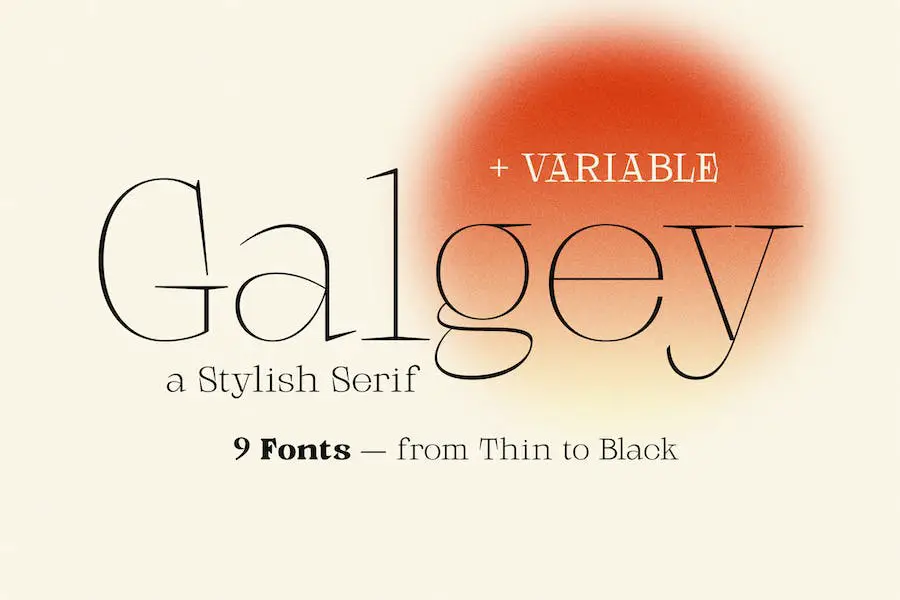
Galgey 是一种时尚的衬线字体,提供 9 种不同的粗细,从细到黑色。 凭借其简洁和现代的设计,无论您是在处理印刷材料还是数字创作,它都是各种设计项目的完美选择。
Galgey 集中的字体经过仔细调整,确保字母之间的最佳间距,并且它们可以在任何程序中使用,无需额外的插件或软件。
该字体集提供了多种选项,允许您尝试不同的粗细和样式,以获得适合您的项目的外观。 无论您想要精致优雅的美感,还是大胆而有影响力的设计,Galgey 都能满足您的需求。
Galgey 的主要优势之一是它的简单性。 简洁的线条和简约的字体使其即使在较小的尺寸下也非常清晰易读。
这使得 Galgey 成为编辑布局中正文以及需要产生强烈影响的标题和标题的绝佳选择。 该字体的现代和永恒的设计确保它永远不会过时。
勇士
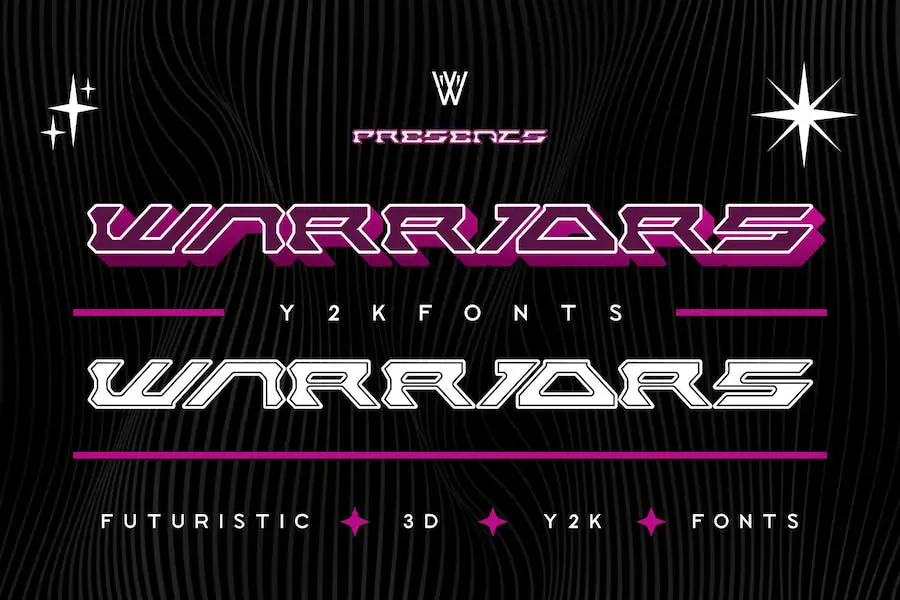
Warriors 是一种散发着未来主义和赛博朋克风格印象的字体,使其成为创建引人注目的海报设计的完美选择。 其独特的功能和美观使其有别于市场上的其他字体。
Warriors 字体拥有现代而前卫的外观,具有锐利的角度和流畅的线条。 这种字体旨在吸引注意力并在任何项目中发表声明。
无论您是在制作活动、促销海报还是平面设计作品,《Warriors》都能增添一丝前卫的魅力。
勇士队的突出特点之一是它的多功能性。 这种字体可用于多种设计,从粗体标题到时尚的正文。 其时尚且充满未来感的外观使其成为科幻或科技主题项目的绝佳选择。
此外,它还可以与各种配色方案完美配合,让您可以尝试并创造出视觉上令人惊叹的作品。
有缺陷的
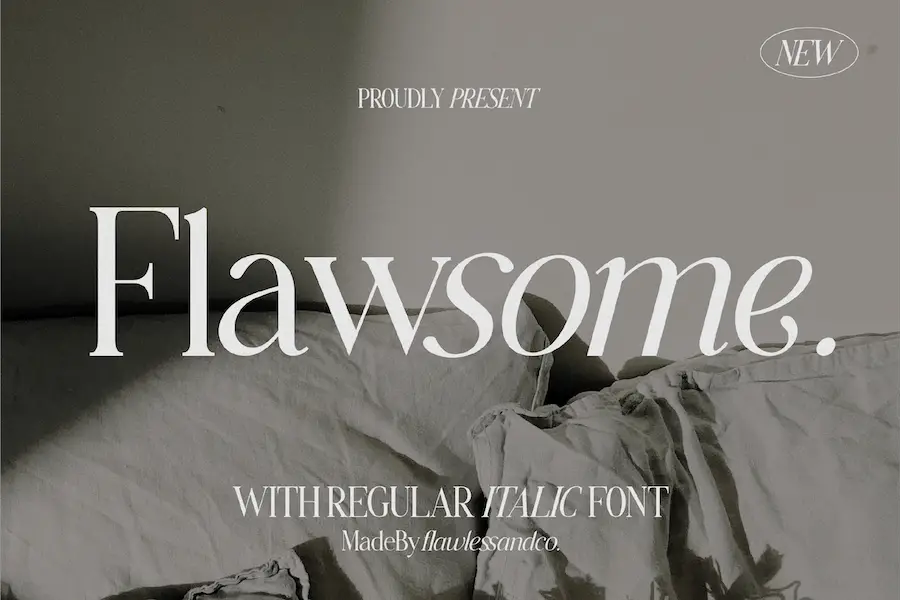
隆重推出 Flawsome,这是一种常规斜体衬线字体,可为您的设计项目带来现代和千禧一代的感觉。 这种字体组合用途广泛,可以在各种平台上使用。
凭借其优雅奢华的外观,它非常适合创建徽标和品牌材料。
Flawsome 字体具有区别于其他字体的独特魅力。 其规则的斜体风格为您的设计增添了一丝精致和创造力。 无论您是从事专业项目还是个人项目,这种字体都会提升整体外观和感觉。
Flawsome 的一大优点是它与 Canva、Procreate 和 Cricut 等流行设计软件的兼容性。 这使得它非常易于使用并融入您的设计工作流程。 您可以使用此字体轻松创建令人惊叹的图形、数字艺术,甚至剪贴画。
爱无所不在
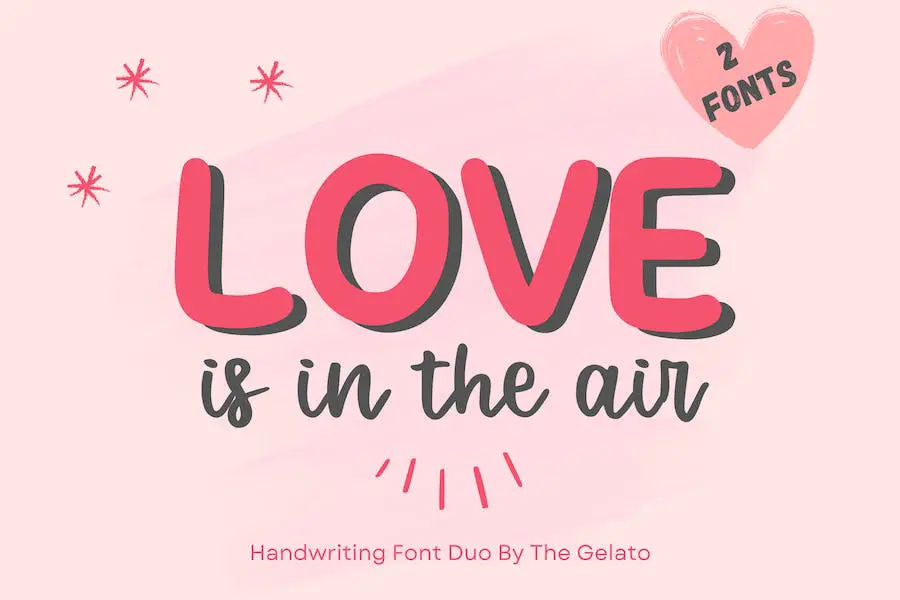
Love Is In The Air 是一套字体配对集,结合了两种令人惊叹的手写书法和单线粗体手写字体。 借助这款字体组合,您可以轻松为您的设计项目增添一丝优雅和浪漫。
该集中的第一个字体是一个漂亮的手写书法字体。 它散发着女性气质和优雅感,非常适合制作婚礼请柬、情书或任何需要浪漫气息的项目。 其流畅的笔触和精致的曲线将立即提升您的设计。
第二种字体是单线粗体手写字体。 它为您的设计增添了现代感和现代感,非常适合增添一些冲击力和风格。
无论您是在制作徽标、品牌还是社交媒体图形,这种字体都将使您的文本以其大胆而自信的外观脱颖而出。
《Love Is In The Air》中的两种字体完美互补,在优雅与大胆之间创造出和谐的平衡。 无论是一起使用还是单独使用,它们都会为您的设计增添独特而引人注目的元素。
韦伯鲁什
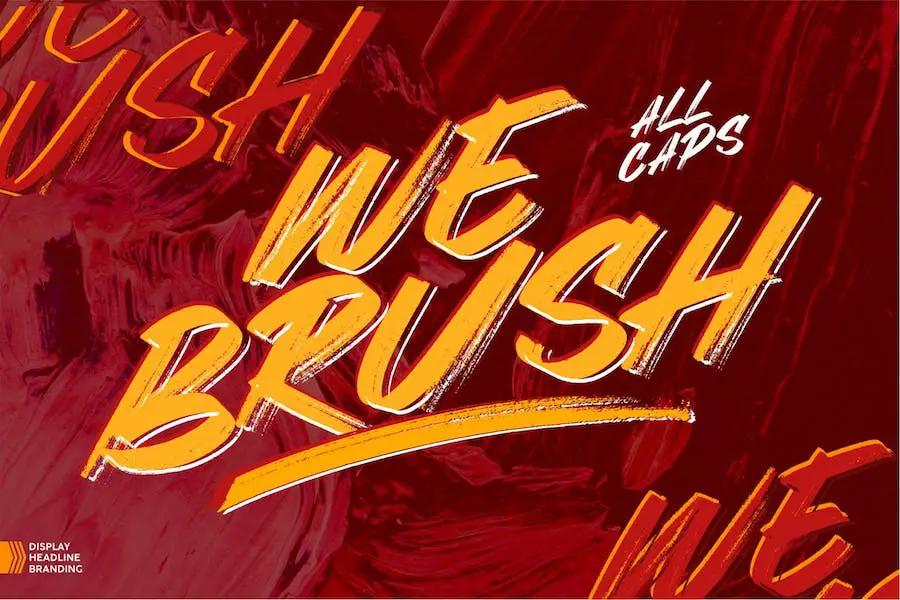
隆重推出 Webrush,这是一款 Procreate 字体,它将迷人的曲线与清新的城市边缘融为一体。 这个时尚的脚本非常适合增强您的徽标设计、商品和社交媒体帖子。 凭借其引人注目的吸引力,Webrush 一定会让您的项目脱颖而出。
Webrush 的优点之一是它的多功能性。 无论您是想创建一个现代徽标还是为您的社交媒体帖子添加一丝优雅,这款字体都能满足您的需求。 其迷人的曲线赋予其独特而时尚的外观,非常适合任何设计项目。
Webrush 的另一个优点是它能够为您的设计添加个人风格。 这种字体的手写感觉为您的作品增添了真实感和温暖感,使其更能引起观众的共鸣和吸引力。
它是在您的设计中添加个人引言或信息的完美选择。
格罗克标记
Grock Marker 是一款时尚的画笔标记字体,非常适合为您的创意项目添加自然的触感。 这种独特的字体将手写字体与戏剧性的动作相结合,为您的设计带来精美的手写外观。
无论您正在制作徽标、海报还是任何其他创意项目,Grock Marker 都会添加您正在寻找的额外风格。 其自然有机的风格非常适合吸引注意力并给人留下持久的印象。
凭借其易于使用的格式,您可以使用 Procreate 将 Grock Marker 无缝融入您的设计中。 告别无聊的通用字体,并利用 Grock Marker 的魅力和个性提升您的项目。
吉布拉内
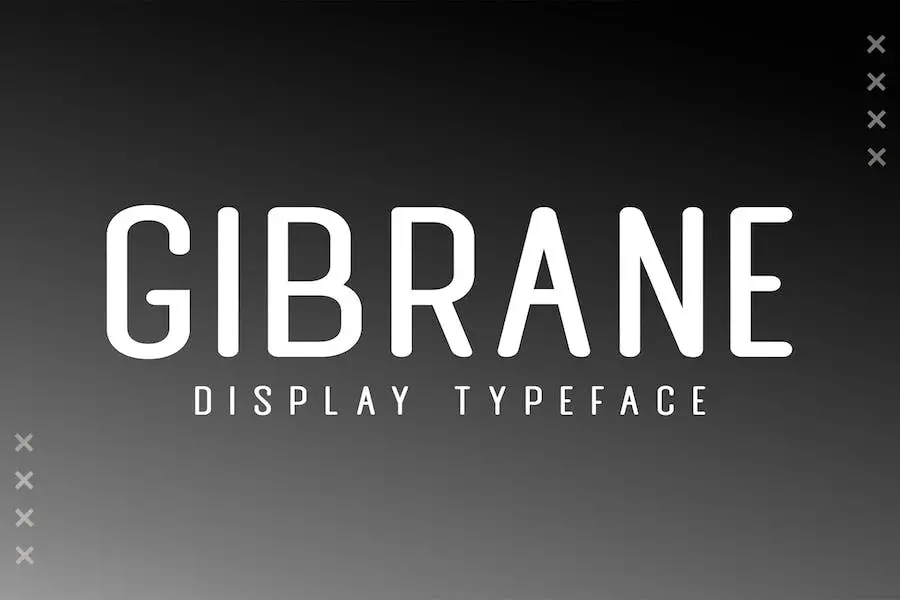
Gibrane 是一种多功能字体,可用于各种设计项目。 它非常适合品牌推广、生育、装饰工艺品、邀请函等!
凭借其全大写字形、数字、基本标点符号和多语言支持,该字体为图形设计师提供了广泛的可能性。
无论您是创建徽标、设计海报还是制作个性化邀请函,Gibrane 都能满足您的需求。 其时尚的设计将增强您项目的整体外观和感觉,使它们脱颖而出。
狂野之心
Wild Heart 是一种现代手写字体,可为您的设计增添创意和优雅。 凭借其独特的艺术天赋,这种字体非常适合希望通过个人风格增强其项目的图形设计师。
《狂野之心》的属性使其如此吸引人。 其流畅流畅的线条赋予其自然有机的感觉,同时仍保持现代感。 每个字母对细节的关注是显而易见的,使其成为一种多功能字体,可用于各种设计目的。
《狂野之心》的突出特点之一是它传达情感和个性的能力。 无论您是在制作徽标、品牌材料还是社交媒体图形,这种字体都将帮助您捕捉信息的精髓,并对受众产生持久的影响。
工艺拼贴
Craft Collage 是一种从旧剪报的复古魅力和流行的拼贴趋势中汲取灵感的字体。 凭借其复古氛围,这种字体是希望通过怀旧和艺术天赋来增强其项目的图形设计师的完美选择。
Craft Collage 的独特设计为任何文本增添了复古和手工制作的感觉,使其成为复古主题设计或需要独特且引人注目的排版的项目的理想选择。
无论您是在制作海报、专辑封面还是社交媒体图形,Craft Collage 都一定会以其永恒的吸引力提升您的设计。 通过工艺拼贴发挥创意并带回昔日的魅力。
快的
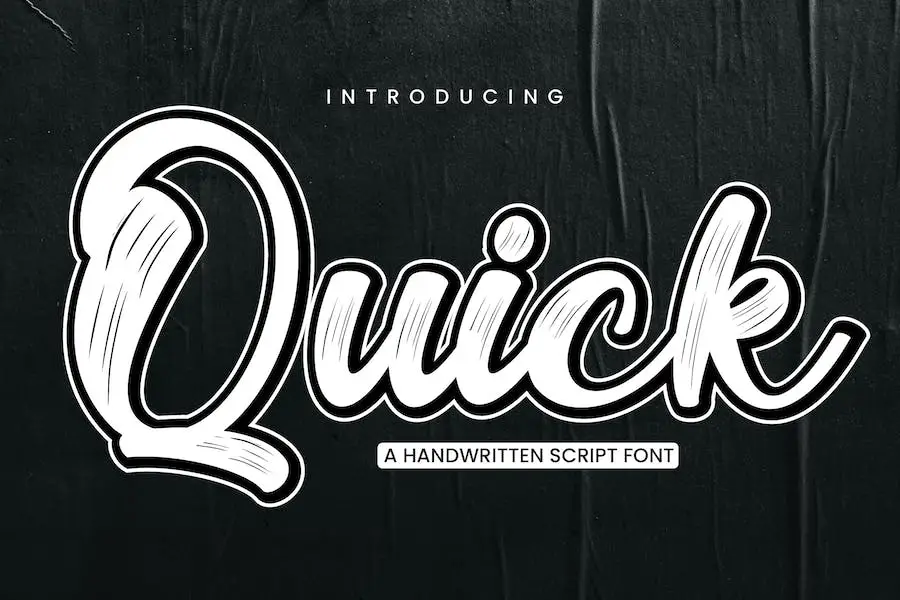
Quick 是一款脚本画笔字体,专为创建黑板引言和教材而设计。 凭借其真实的外观,它为任何设计项目增添了个性化和现实的感觉。 该字体采用 PUA 编码,可以轻松访问其所有字形和花体。
这种脚本画笔字体非常适合想要通过手绘风格增强其项目的图形设计师。 无论您是在制作教育材料、励志名言还是宣传材料,Quick 都可以为您的设计带来独特的艺术风格。
Quick 的突出特点之一是其真实的笔触,赋予字体自然和有机的感觉。
这些笔触增加了深度和纹理,使您的文本脱颖而出并引人注目。 该字体的脚本风格也为任何设计增添了优雅和精致的感觉。
马洛
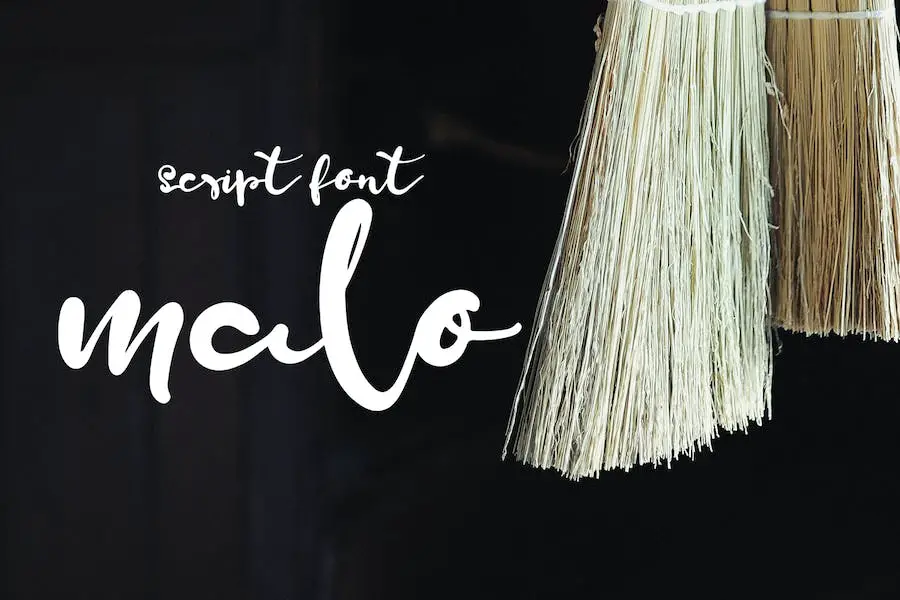
malo 是一种令人愉悦的脚本字体,捕捉了手写字体的精髓。 它具有流畅、刷子般的品质,可为任何设计增添一丝优雅。 凭借其精心设计的字距调整,这种字体确实感觉就像您在画布上毫不费力地滑动画笔。
malo 的美妙之处在于它能够为您的项目添加有机和个人风格。 无论是徽标、海报还是社交媒体图形,这种字体都带来艺术感和创造力。 其手写风格给人一种独特而有质感的外观,在人群中脱颖而出。
malo 的突出特点之一是它的多功能性。 它可用于各种设计目的,使其成为任何图形设计师工具包的宝贵补充。 流畅流畅的笔触使其成为理想的工作方式,让您轻松创建令人惊叹的版式。
父亲的恳求
Father's Entreaty 是一种迷人的手写字体,可为您的设计项目带来古怪而独特的风格。 其俏皮而独特的字体为任何设计增添了一丝个性和特色。
有了父亲的恳求,您可以轻松创建引人注目的排版,在人群中脱颖而出。
这种字体非常适合希望使用既具有视觉吸引力又充满个性的字体来提升其项目的图形设计师。 它是创建徽标、标题、海报、社交媒体图形等的绝佳选择。
《Father's Entreaty》以其手绘美学脱颖而出,为您的设计带来真实感和人性化感觉。 这种字体的古怪风格增添了一种异想天开的元素,可以为您的项目注入一丝乐趣和趣味。
叉刷
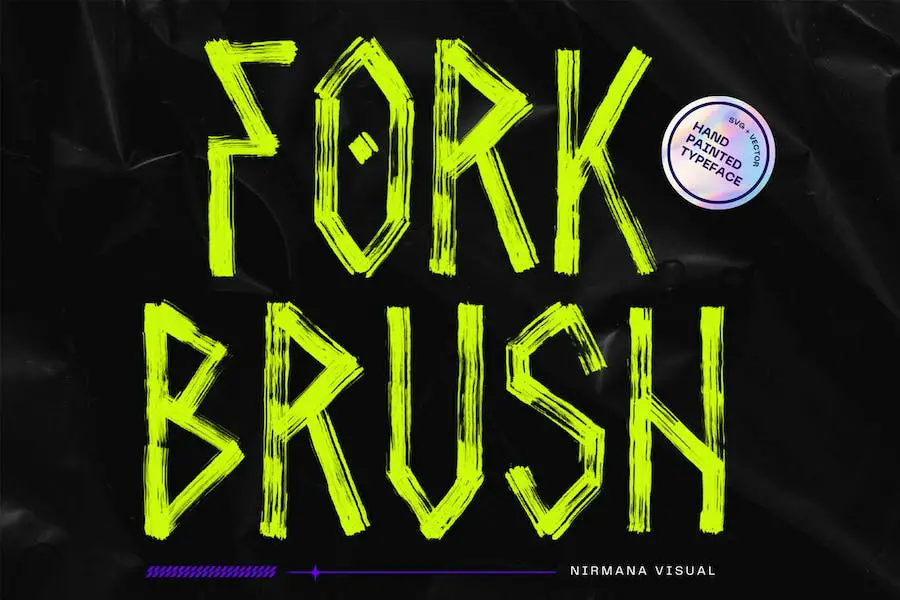
Fork Brush 是一款独特且制作精美的手工刷,可为任何设计项目增添一抹城市街头风格。 这种字体具有多功能的排版和谐性,非常适合从徽标和品牌到社交媒体帖子、广告和产品设计的一系列创意活动。
Fork Brush 的手工制作性质赋予其独特且个性化的感觉,使其成为希望为其作品增添真实感的设计师的绝佳选择。 其城市街头风格营造出前卫和现代的氛围,带来无限的创意可能性。
无论您需要一种能让您的徽标流行的字体,还是想要创建引人注目的社交媒体帖子,Fork Brush 都能满足您的需求。 其和谐的笔触和独特的纹理为任何设计带来深度和个性,而其多功能性确保它可以适应任何项目。
雨林
Rainforest by Salt and Pepper Fonts 是一款可爱的显示字体,可为任何项目增添魅力和个性。 凭借其独特而有趣的设计,它非常适合希望通过一丝奇思妙想来增强其项目的图形设计师。
字体采用手绘风格,给人一种有机、自然的感觉。 无论您是在设计徽标、包装还是社交媒体图形,Rainforest 都一定能让您的设计脱颖而出。
它是一种多功能字体,可用于标题和正文,为您的设计提供灵活性。 总体而言,Rainforest 是一种令人愉悦的字体,可为任何创意项目增添乐趣。
无石
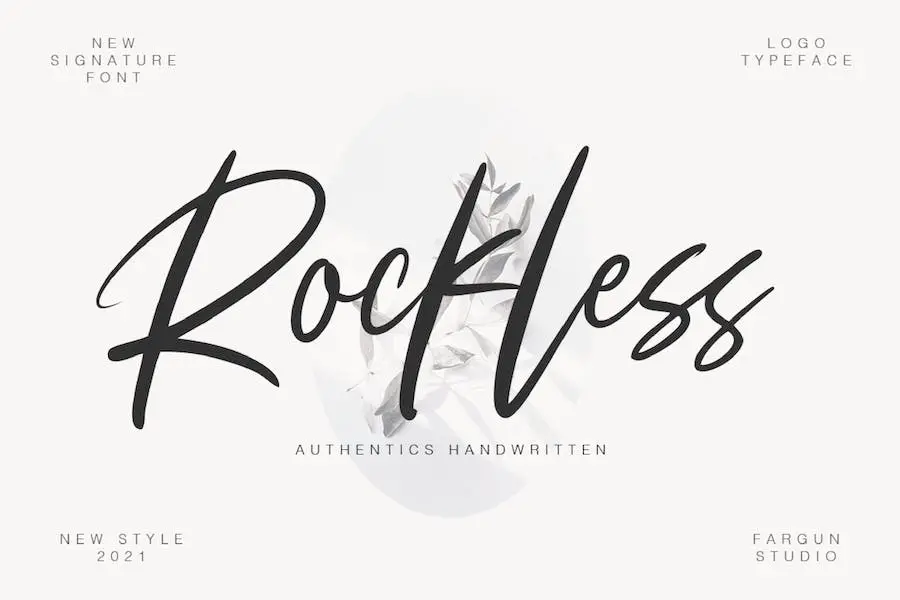
Rockless 是一款手写时尚的铜版书法字体,它将传统铜版字体的美感与现代风格融为一体。
凭借其舞动的基线和经典而优雅的触感,Rockless 是希望增强项目设计的图形设计师的完美选择。
无论您是创建邀请函、徽标还是任何其他类型的设计,Rockless 都会为您的作品添加独特而精致的元素。
其光滑流畅的笔触赋予其自然有机的感觉,使其成为那些寻求更加个性化和艺术触感的人的理想选择。
因此,如果您正在寻找能够将您的设计提升到新水平的 Procreate 书法字体,那么 Rockless 就是您的最佳选择。
雪花
Snowflake 是一款可爱的字体组合,可为您的设计带来有趣和异想天开的感觉。 凭借其手写风格,这种显示字体为任何项目增添了俏皮和欢快的氛围。
无论您是在制作贺卡、海报还是社交媒体图形,Snowflake 都会增强您的设计并使其脱颖而出。
Snowflake 的美妙之处在于它的多功能性。 字体组合包括大写和小写字母,允许您混合搭配以获得独特的外观。 这种字体可爱而欢乐的外观一定会引起人们的注意,并为您的设计带来令人愉悦的魅力。
使用雪花,您可以通过排版轻松传达喜悦和幸福的感觉。 其类似手写的笔画赋予其个性化和相关的感觉,使其非常适合为您的设计增添一丝温暖。
无论您是为孩子的生日聚会创建邀请函,还是为有趣的品牌设计徽标,Snowflake 都能满足您的需求。
戴娜·席尔瓦
Dayna Silva 是一种优雅的脚本字体,可为您的设计增添现代和精致的触感。 凭借其可爱的手写风格,这种字体非常适合时尚品牌、潮流博客、婚礼精品店以及任何想要散发出高档别致美感的企业。
该字体独特的魅力和优雅将立即吸引观众的注意力。 其现代的脚本设计为您的项目增添了个性和艺术感,使它们脱颖而出。
无论您是创建徽标、网站设计还是社交媒体图形,Dayna Silva 都会将您的项目提升到一个全新的水平。
Dayna Silva 的与众不同之处在于其多才多艺。 该字体可以在从印刷到数字的各种设计应用程序中无缝工作。
它增强了时尚相关内容的视觉吸引力,使其成为时尚博主、潮流引领者和行业专业人士的理想选择。 其精致的触感和简洁的线条散发出奢华和时尚的感觉。
德卡莫尔
Dekamor 是一款优雅而现代的字体,可以提升您的设计项目。 这种字体以其时尚而精致的风格,非常适合为您的作品增添一抹优雅。
无论您是创建徽标、设计网站还是开展品牌项目,Dekamor 都将帮助您脱颖而出。
这种字体拥有几个令人印象深刻的属性,使其成为图形设计师的必备字体。 首先也是最重要的是,其干净利落的线条赋予其优雅而专业的外观。 对每个字母形式细节的关注可确保您的文本显得清晰且轮廓分明。
Dekamor 的另一个突出特点是其广泛的字形集。 从大写和小写字母到数字、标点符号和特殊字符,这种字体拥有创建视觉上令人惊叹的设计所需的所有元素。
它甚至提供多种语言支持,使其适合国际项目。
最佳免费 Procreate 字体
希望为您的 Procreate 项目增添一些额外的魅力? 别再犹豫了! 在本节中,我们精选了一系列最好的免费 Procreate 字体,它们一定会让您的设计更上一层楼。
因此,继续探索下面各种独特且时尚的字体,并找到完美的字体来增强您的下一个杰作。 相信我们,您不会失望的!
生育
对于想要提升项目设计的图形设计师来说,Procreate 是一款出色的工具。 它提供了多种字体,可以增强任何设计的视觉吸引力。 使用 Procreate,您可以轻松找到完美的字体,使您的创作脱颖而出。
Procreate 的一大优点是它免费供个人使用。 这意味着设计师可以探索和尝试不同的字体,而无需任何财务承诺。
这是发现新的排版风格并扩展您的创意视野的绝佳机会。
Procreate 中提供的字体由才华横溢的设计师 Sugeng Choirul 精心策划。 每种字体都因其独特的特征和视觉冲击力而被选择。 无论您正在寻找时尚现代还是优雅经典的东西,您都可以在 Procreate 中找到它。
生育者
Erik Studio 的 Procreate 是一款改变游戏规则的工具,适合希望增强项目设计的图形设计师。 该字体包有 27 种令人惊叹的字体可供选择,非常适合为任何设计增添额外的风格和专业精神。
这些字体由顶级设计师精心制作,以确保最高的质量和多功能性。 从优雅的脚本到大胆而现代的无衬线字体,每种项目和风格都有一种字体。 Procreate 提供多种选项以满足任何设计需求。
Procreate 的最佳功能之一是其易用性。 只需点击几下,您就可以在 Procreate 应用程序中安装并开始使用这些令人惊叹的字体。 无需复杂的设置或额外的步骤。 它快速且无忧,让您可以专注于您最擅长的事情 - 设计。
Procreate 字体还与其他设计软件和程序完全兼容,使其成为任何设计师工具箱的多功能且有价值的补充。
无论您是在处理数字插图、品牌项目还是营销材料,这些字体都会将您的设计提升到一个新的水平。
生育签名
Procreate Signature 是一款令人印象深刻的字体,非常适合希望提升项目设计的图形设计师。 该字体由 Febryl Arully 创建,具有独特而时尚的触感,可以增强任何创意工作。
Procreate Signature 字体拥有时尚而现代的设计,使其成为各种项目的理想选择。 其简洁的线条和优雅的曲线为任何文本赋予专业和优雅的外观。
无论您是设计徽标、制作海报还是创作数字艺术品,这种字体都会为您的作品增添一丝精致和精致。
Procreate Signature 的突出特点之一是它的多功能性。 有多种款式和重量可供选择,您可以轻松找到适合您项目需求的完美选择。
无论您喜欢大胆、引人注目的外观还是更微妙、低调的风格,这款字体都能满足您的需求。
超级欢乐时光
Super Funtime 是一款出色的字体,非常适合为您的图形设计项目增添一丝乐趣和个性。 该字体由 fsuarez913 创建,具有独特而俏皮的风格,一定会吸引观众的眼球。
借助 Super Funtime,您可以为您的设计带来令人愉悦的变化,并使其在人群中脱颖而出。
Super Funtime 的突出特点之一是它的多功能性。 无论您是在制作海报、徽标,甚至是社交媒体图形,都可以通过多种方式使用此字体来增强整体设计。
其异想天开和活泼的性格增添了一丝魅力和创造力,使您的设计更加令人难忘和吸引人。
Super Funtime 的另一个重要功能是其广泛的字形和连字选择。 借助多种替代字符,您可以轻松自定义和尝试不同的字母组合,以获得完美的外观。
这种字体让您可以自由地创建独特且引人注目的排版,真正反映您的个人风格。
酵母味
Niskala Huruf 的 Yeasty Flavors 是一款肯定会提升您的设计项目的字体。 凭借其独特而引人注目的风格,该字体将为任何项目增添一丝精致和创造力。
无论您是在设计徽标、品牌,甚至是社交媒体图形,Yeasty Flavors 都是完美的选择。
酵母口味的突出特点之一是其多功能性。 这种字体可用于标题和正文,使其成为创建有凝聚力和精美设计的绝佳选择。
这种字体简洁的线条和优雅的曲线为您的设计带来现代和专业的外观。
除了多功能性之外,Yeasty Flavors 还提供各种重量和风格。 从大胆、戏剧性到微妙、低调,这种字体有多种变体,可以满足各种设计需求。
无论您想要时尚简约的美学还是大胆引人注目的外观,Yeasty Flavors 都能满足您的需求。
安抚愤怒
Niskala Huruf 的 Pacify Angry 是一款多功能且有影响力的字体,非常适合希望增强其项目的图形设计师。 凭借其独特而引人注目的风格,Pacify Angry 为任何设计增添了一丝创造力和天赋。
这种字体具有粗体和强烈的字母形式,可以吸引注意力并传达力量感。 其锋利的边缘和简洁的线条赋予其现代前卫的外观,使其成为当代设计的理想选择。
《平息愤怒》易于阅读,让您的受众能够清楚地了解您的信息。 无论您是设计徽标、海报还是网站,这种字体都将帮助您的文本脱颖而出并产生影响。
Pacify Angry 有多种重量和款式可供选择,为您的设计提供无限的可能性。 从大胆和自信到微妙和精致,这种字体拥有一切。 它允许您尝试不同的外观并创作独特的作品。
发霉的奶酪
Moldy Cheese 由 Niskala Huruf 设计,是一种独特且引人注目的字体,非常适合希望为其项目增添个性的图形设计师。 凭借其前卫且非传统的设计,Moldy Cheese 为任何设计增添了古怪而有趣的元素。
这种字体提供了广泛的属性,使其具有高度的通用性。 其大胆而不均匀的字体散发出叛逆和不拘一格的氛围,使其成为需要个性化项目的绝佳选择。
无论您是在制作徽标、海报还是网站,发霉奶酪一定会脱颖而出并吸引注意力。
发霉奶酪的不规则形状和粗糙边缘赋予其手工制作和有机的感觉,为您的设计增添深度和质感。 即使在较小的尺寸下,它也具有很高的可读性,使其适合标题和正文。
阳光咒语
Niskala Huruf 的 Sunny Spells 是一款令人难以置信的字体,它将成为任何图形设计师工具包的绝佳补充。 凭借其时尚而现代的设计,它非常适合为任何项目增添一丝优雅。
这种多功能字体具有多种样式和粗细,使设计师能够创造出独特且引人注目的设计。
Sunny Spells 的突出特点之一是它的可读性。 简洁的线条和明确的字体使观众很容易与文本互动并掌握所传达的信息。
无论是在徽标、网站还是社交媒体帖子中,这种字体都将确保您的文本清晰易读。
Sunny Spells 的另一个重要特性是它的多功能性。 它可用于广泛的设计项目,从品牌和包装到广告和编辑。
凭借其现代和时尚的美感,该字体可以适应任何设计理念,增添一丝精致和专业精神。
维迪·古斯蒂
Widie Gusti 是由 Miftaharzaq 设计的独特且多功能的字体。 这种字体为您的图形设计项目带来新鲜和现代的感觉,使它们脱颖而出。
Widie Gusti 凭借简洁的线条和时尚的曲线,为任何设计增添一抹精致。 无论您是在创建徽标、海报还是社交媒体图形,这种字体一定会吸引观众的眼球。
Widie Gusti 的突出特点之一是其广泛的字形和连字。 这使您可以创建视觉上有趣且有凝聚力的设计,而无需任何额外的努力。 该字体还具有不同的粗细,使您的设计选择更加灵活。
Widie Gusti 的另一个重要特点是它的可读性。 这些字母间距良好且易于阅读,非常适合印刷和数字设计。 还值得一提的是,该字体与 Procreate 完全兼容,使其可以轻松使用并合并到您的项目中。
经常问的问题
Procreate 是一款数字艺术应用程序,允许艺术家在 iPad 或 iPhone 上创建和设计插图、绘画和其他艺术项目。 它提供了广泛的工具和功能,使其成为艺术家和设计师的热门选择。
结论
在这篇博文中,我们探索了 27 种可以提升项目设计的最佳 Procreate 字体。 从优雅的脚本字体到大胆现代的风格,我们提供了一系列选项来满足不同的设计偏好。
无论您是专业的图形设计师还是只是想增强您的创意项目,这些字体一定会激发您的灵感。